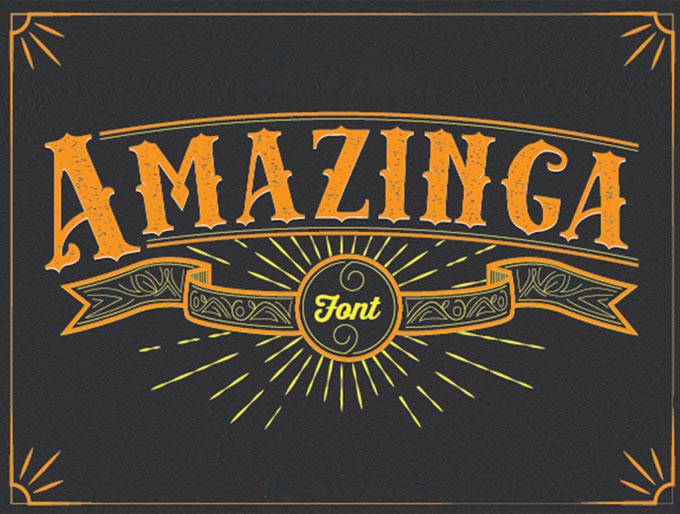
معرفی Amazinga Typeface، نمایش فونت serif. این طراحی پرنعمت به شدت توسط زیبایی جسورانه دوره ویکتوریا الهام گرفته شده است برای پوسترها، برچسب ها، آرم ها، نمایش ها و خیلی بیشتر!